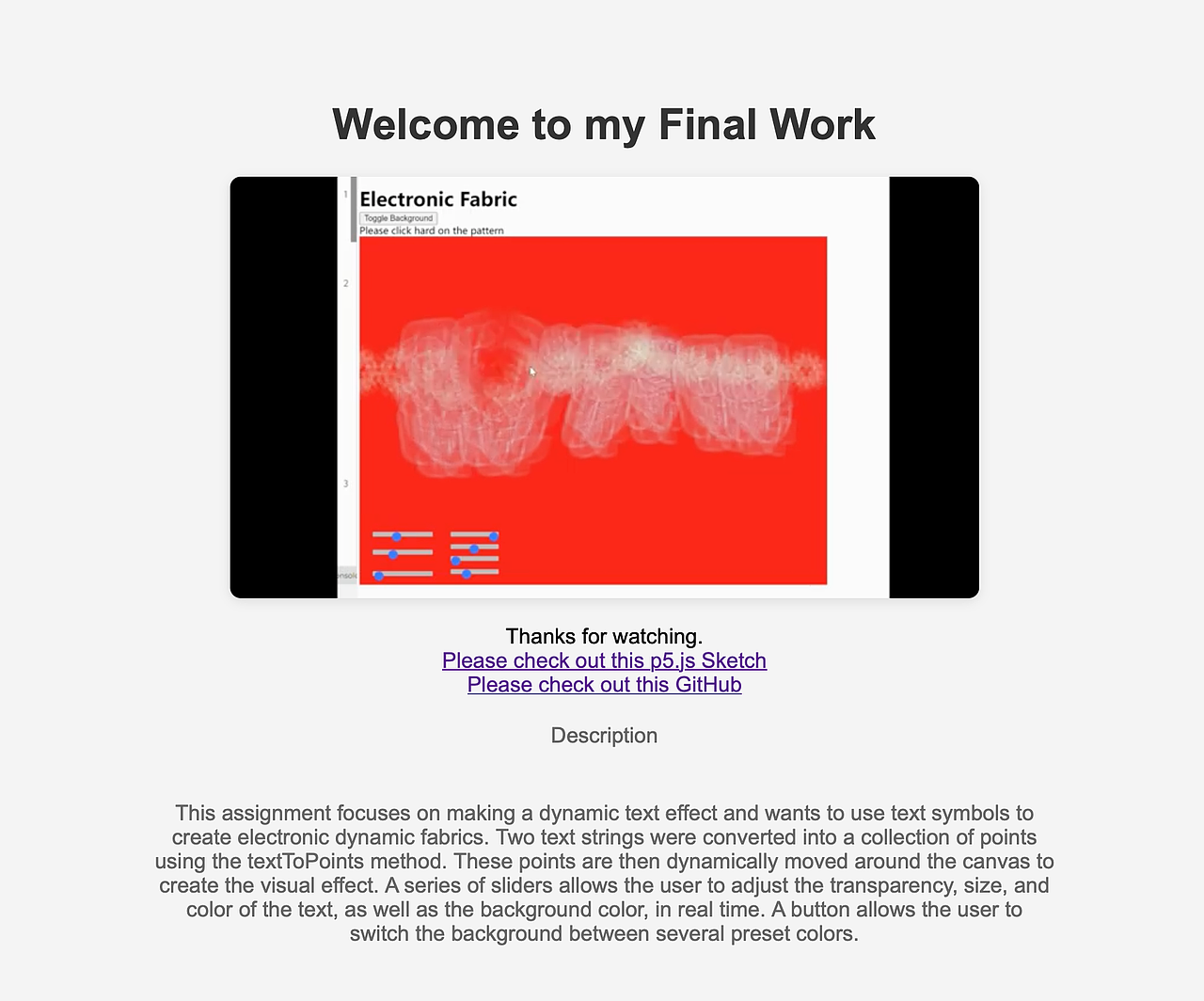
字体视觉设计 *解压电子布料*(P5js算法生成)
输入文字为&&*&*&*&&得出的视觉结果
更改背景颜色
部分代码
本作业的重点是制作动态文本效果,并希望使用文本符号来制作电子动态织物。使用P5js的代码来生成动态视觉。
通过一系列滑块,用户可以实时调整文字的透明度、大小、颜色以及背景颜色。通过一个按钮,用户可以在几种预设颜色之间切换背景。